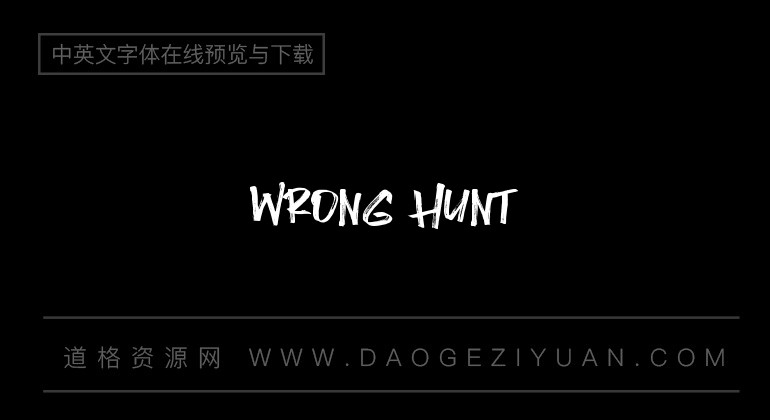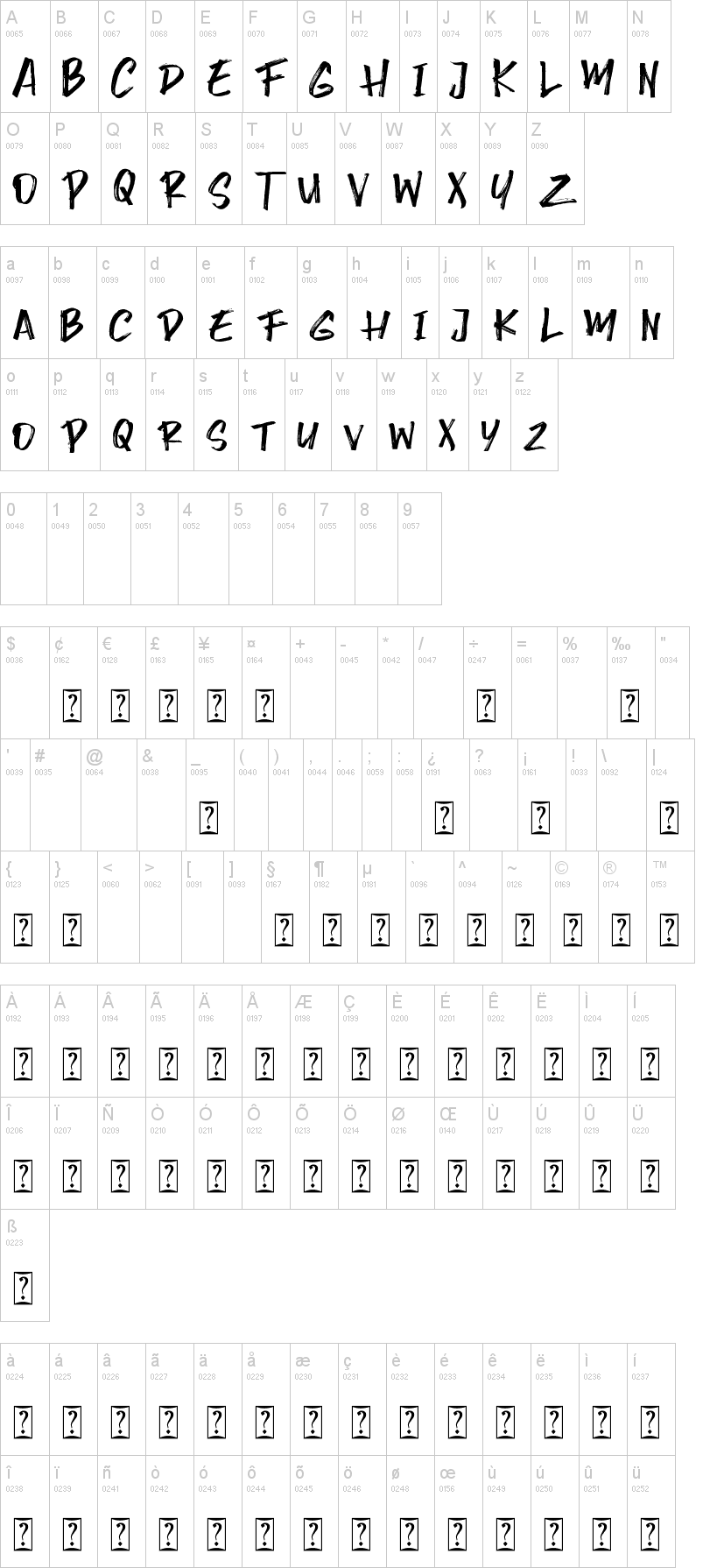
Wrong Hunt是一种独特的手写风格字体,它的特点是字母之间的间距很小,笔画非常粗糙,看起来就像是被手写在一张纸上的。字体包含大写字母、小写字母、数字和一些标点符号。Wrong Hunt字体的设计者是一个名叫Lukas Jech的设计师,他的设计风格以简洁、现代和实用为特色。这款字体适合用于海报、印刷品、标志和其他需要突出个性化的设计项目。内容介绍
Wrong Hunt是一款非常不错的手写艺术字体,具有很好的视觉感,适合于文化类的宣传设计、商业类品牌的广告和产品包装设计以及个性化文字排版等较多场景。